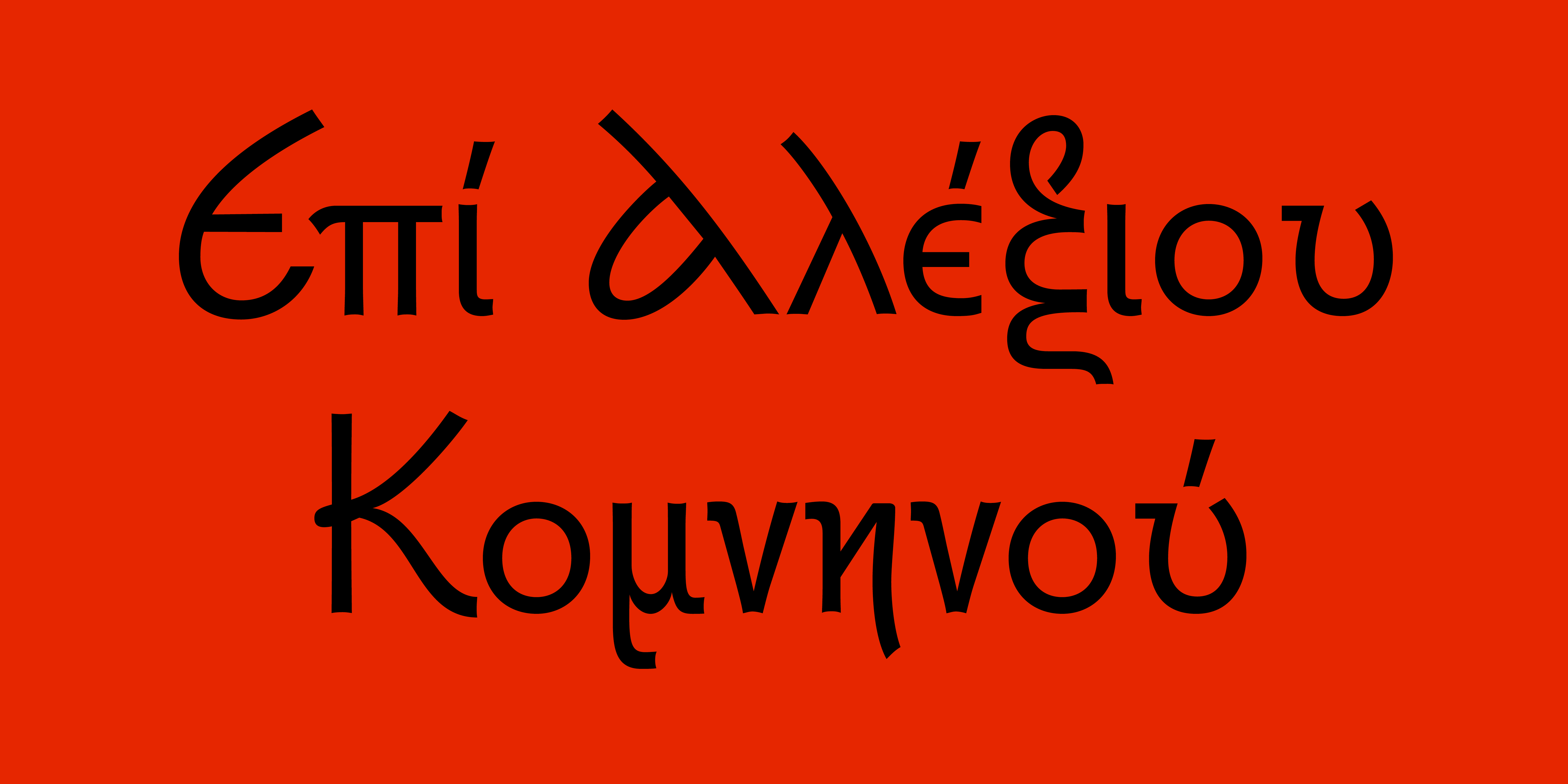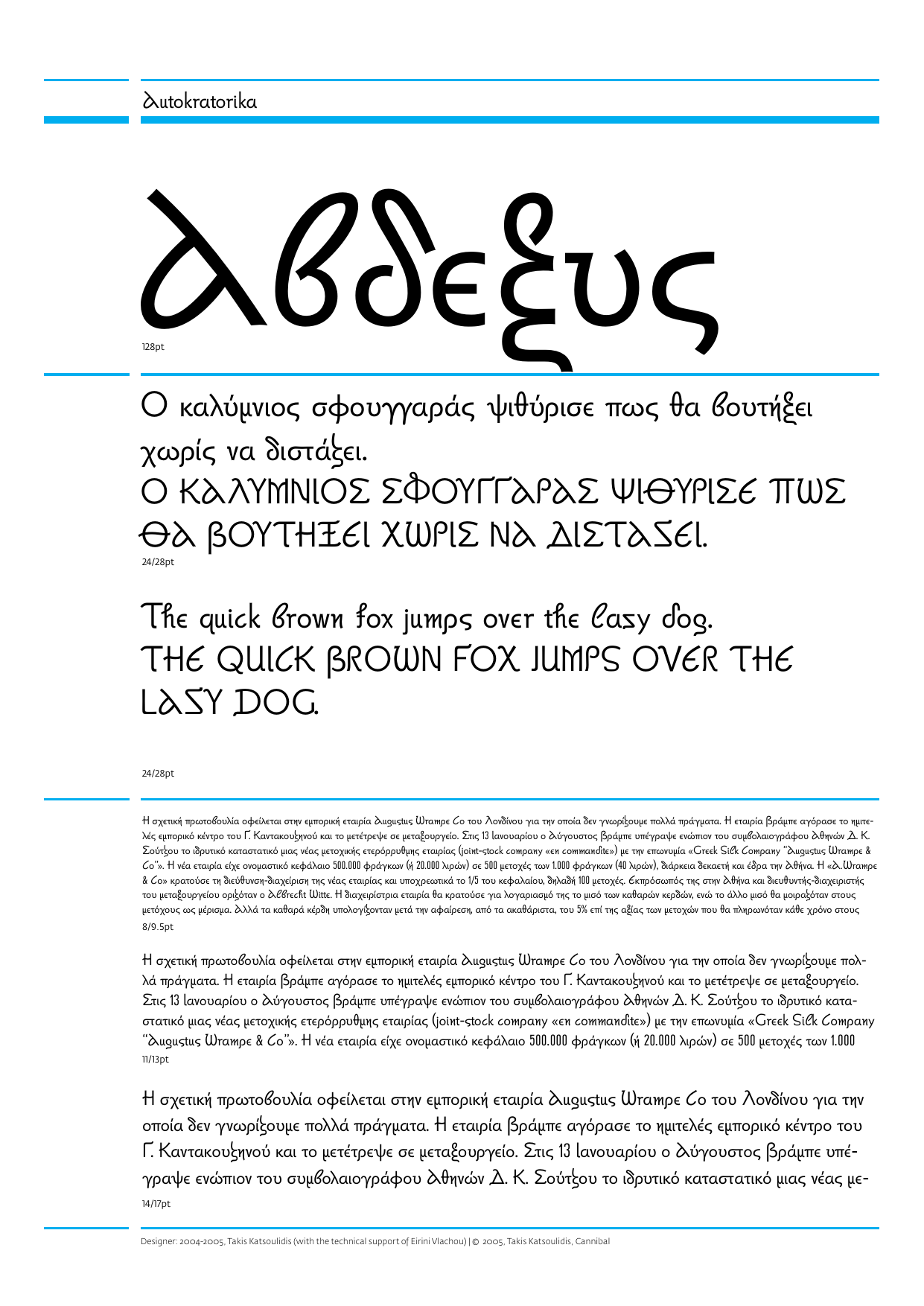
Autokratorika
Προορίζεται κατά κύριο λόγο για λογοτεχνικά κείμενα, ενώ οι ρίζες της χάνονται κάπου στον 11ο αιώνα. Ο Τάκης Κατσουλίδης έχοντας επιμεληθεί το 1980 ένα λεύκωμα με τα Αυτοκρατορικά έγγραφα της Πάτμου για το Εθνικό Ίδρυμα Ερευνών (με τη συνδρομή και της Έρας Βρανούβη);, παρατήρησε ότι οι γραφές αυτές έχουν έναν ιδιόμορφο, δικό τους χαρακτήρα που του κέντρισε το ενδιαφέρον. Έτσι, επανήλθε σε αυτά αργότερα επιλέγοντας ένα από τα έγραφα, και συγκεκριμένα το Χρυσόβουλον Νικηφόρου Γ’ του Βοτανειάτου του 1079, και το χρησιμοποίησε ως πρότυπο για τη γραμματοσειρά του. Τα Αυτοκρατορικά έγγραφα της Πάτμου είναι κείμενα που αντάλλασσαν οι Βυζαντινοί Αυτοκράτορες με τις μονές. Πρόκειται για ανεξάρτητα τετρασέλιδα που λέγονταν και “Χρυσόβουλα” και το περιεχόμενό τους αφορούσε οδηγίες προς άλλα βυζαντινά κέντρα. «Είδα ότι αυτή η γραφή, όπως και εκείνη των Κομνηνών, είναι μια γραφή που περνάει μέσα από την καρδιά του Βυζαντίου, από τον 11ο αιώνα», λέει ο Τάκης Κατσουλίδης. «Παρ’ όλα αυτά δεν είναι τα βυζαντινά γράμματα όπως τα ξέρουμε, κάποια είναι πιο στρογυλά ενώ άλλα είναι πολύ στενά. Αυτόν το χαρακτήρα προσπάθησα να τον κρατήσω κι εγώ». Τα “Αυτοκρατορικά” είναι μια ισοπαχής γραμματοσειρά, με πολύ μικρό οφθαλμό και εξάρσεις στα ανωφερή στοιχεία.